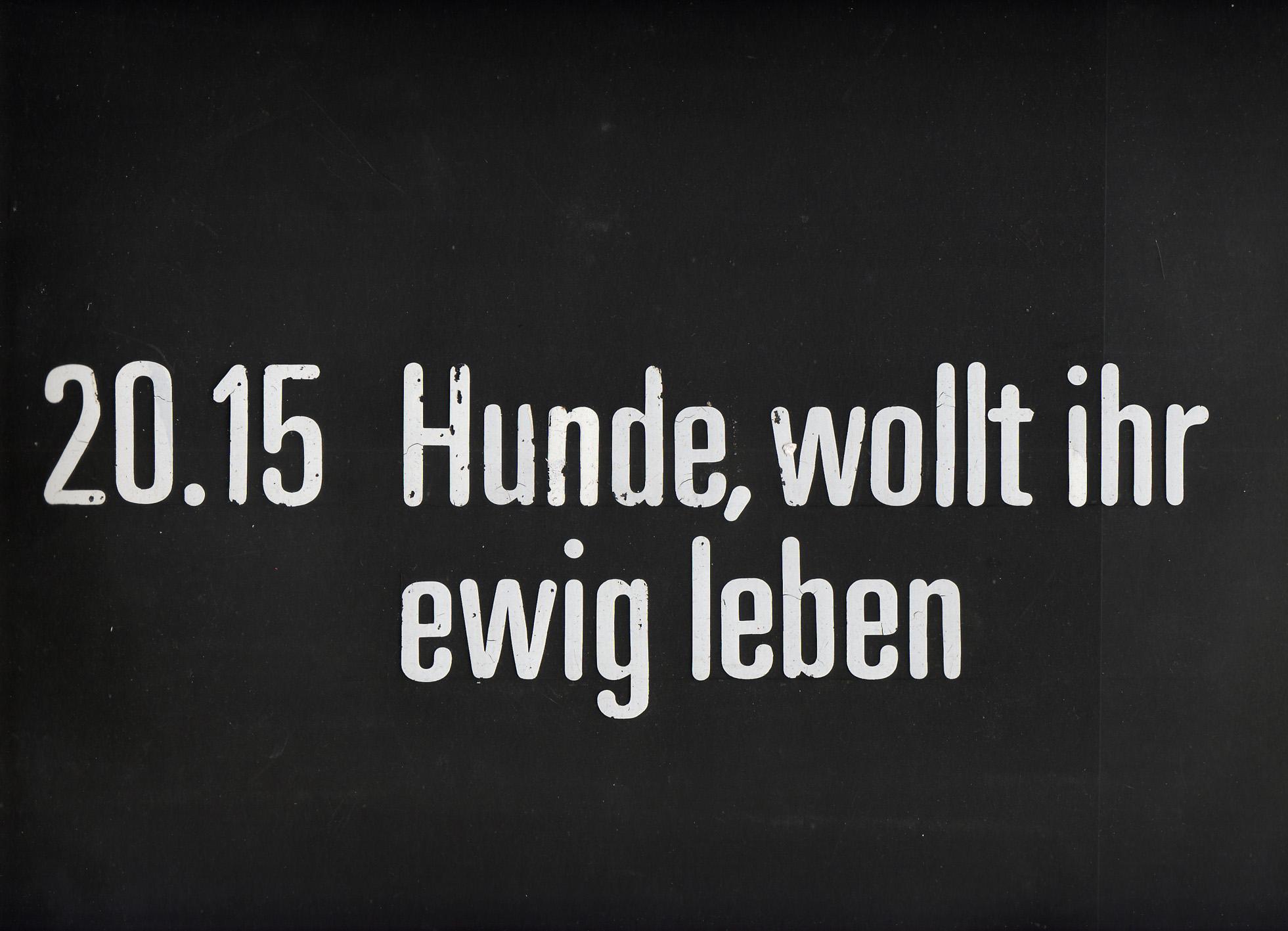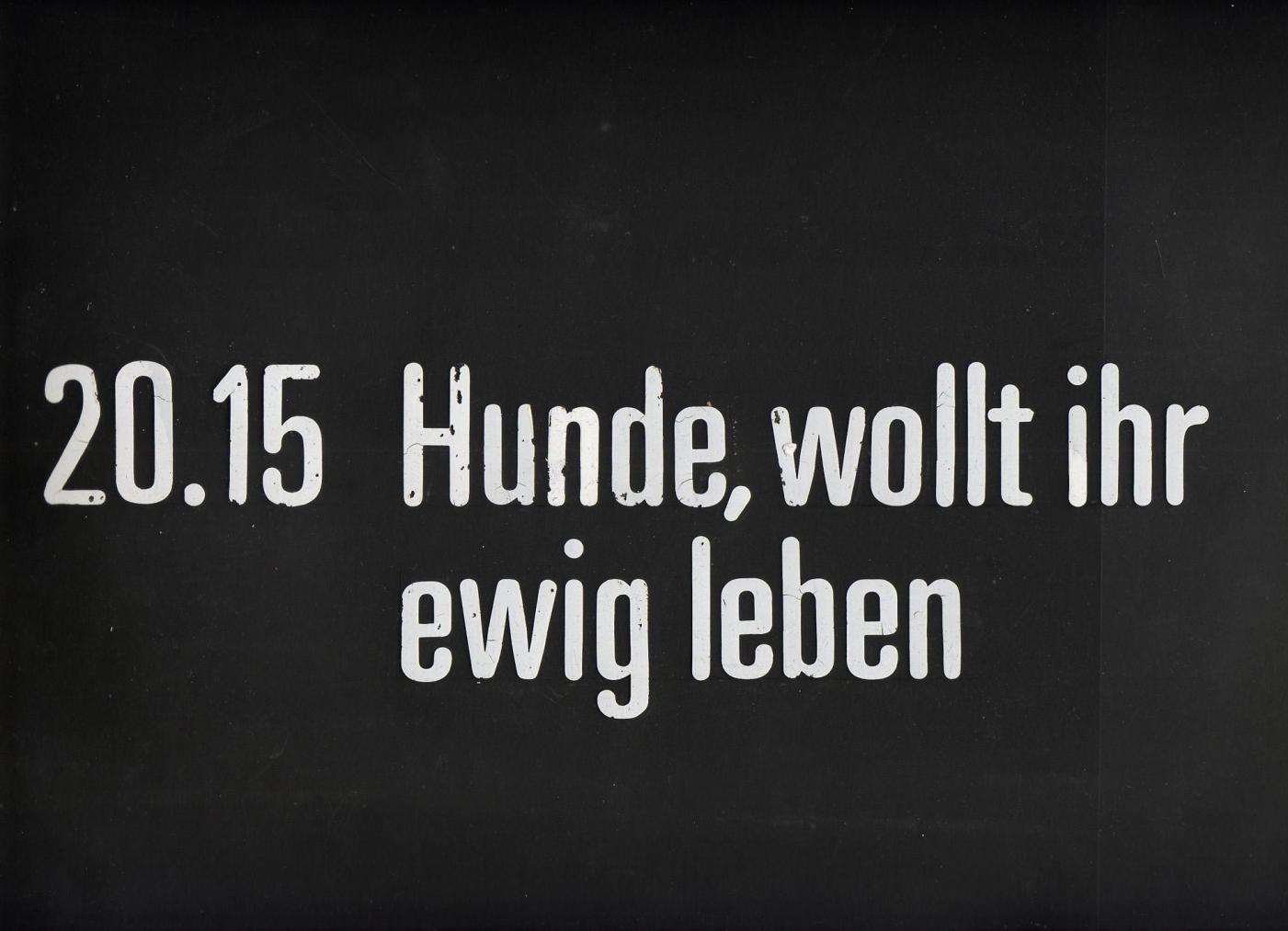
Abgerundete Schmalschrift - als Letraset
Anbei ein Scan eines matttransparenten DIN-A-3-Bogens, auf dem eine weiße Schrift aufgerieben wurde: eine angerundete Schmalschrift. Welche Schrift ist das? Es ist nicht die HELVETICA, nicht die ACCIDENZ-GROTESK.
Sieht aus wie die ZDF-Hausschrift aus den 7oern (eine nach Art der VAG abgerundete Univers).
An eine abgerundete Univers dachte ich auch beim ersten Anblick ... aber erst das Stichwort ZDF verhalf mir zum Sucherfolg.
In 1972 Otl Aicher and his team designed four weights of a round Univers for the Zweites Deutsches Fernsehen (Second German Television).
Da gibt es schöne Beispielbilder ... aber keinen richtigen Namen ... Und eine Quellenangabe: SPIEGEL 33/1973 ...
Hier der SPIEGEL 33/1973 zum Thema: ZFF: Sprung ins Wasser:
Otl Aicher hat also die Schrift seines Freundes Adrian Frutiger, die Univers, zugrunde gelegt und
die abgerundete Fassung kreiert.
Außer den Letraset-Bogen mit den verschiedenen Fetten und Breiten gibt es wohl keine "font-taugliche" Fassung.
Das ZDF hat sich die Schrift ja sichern lassen.